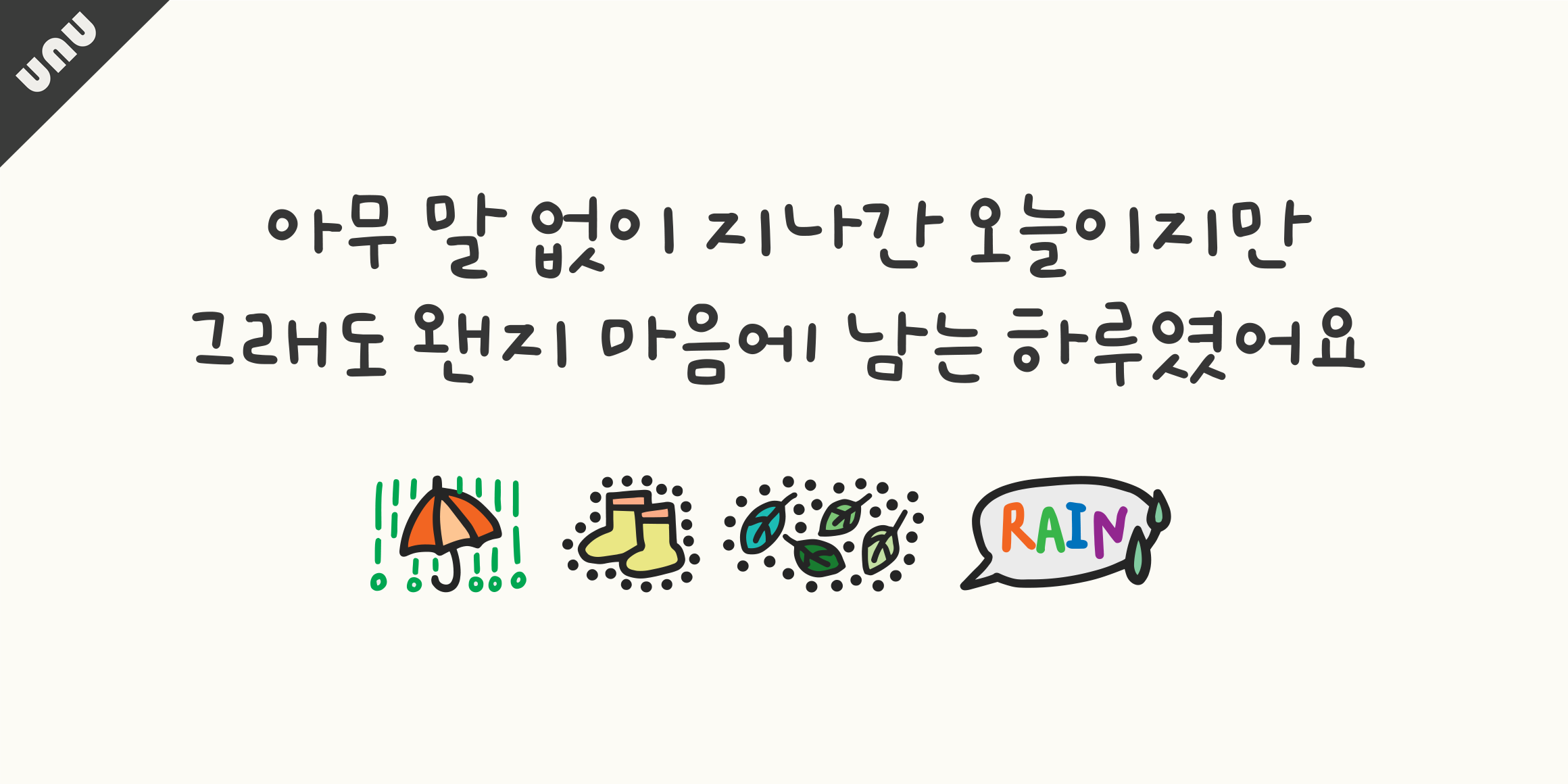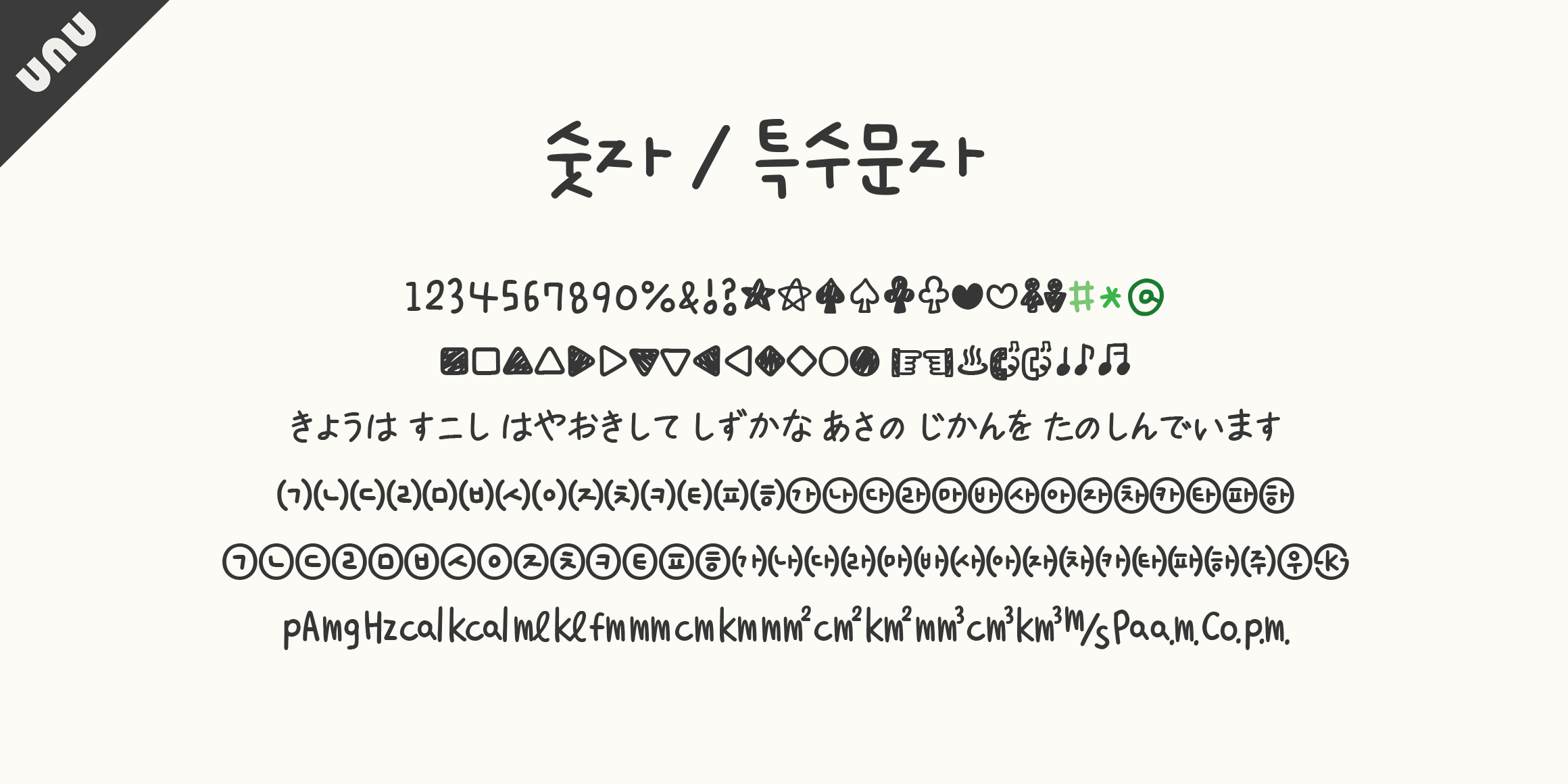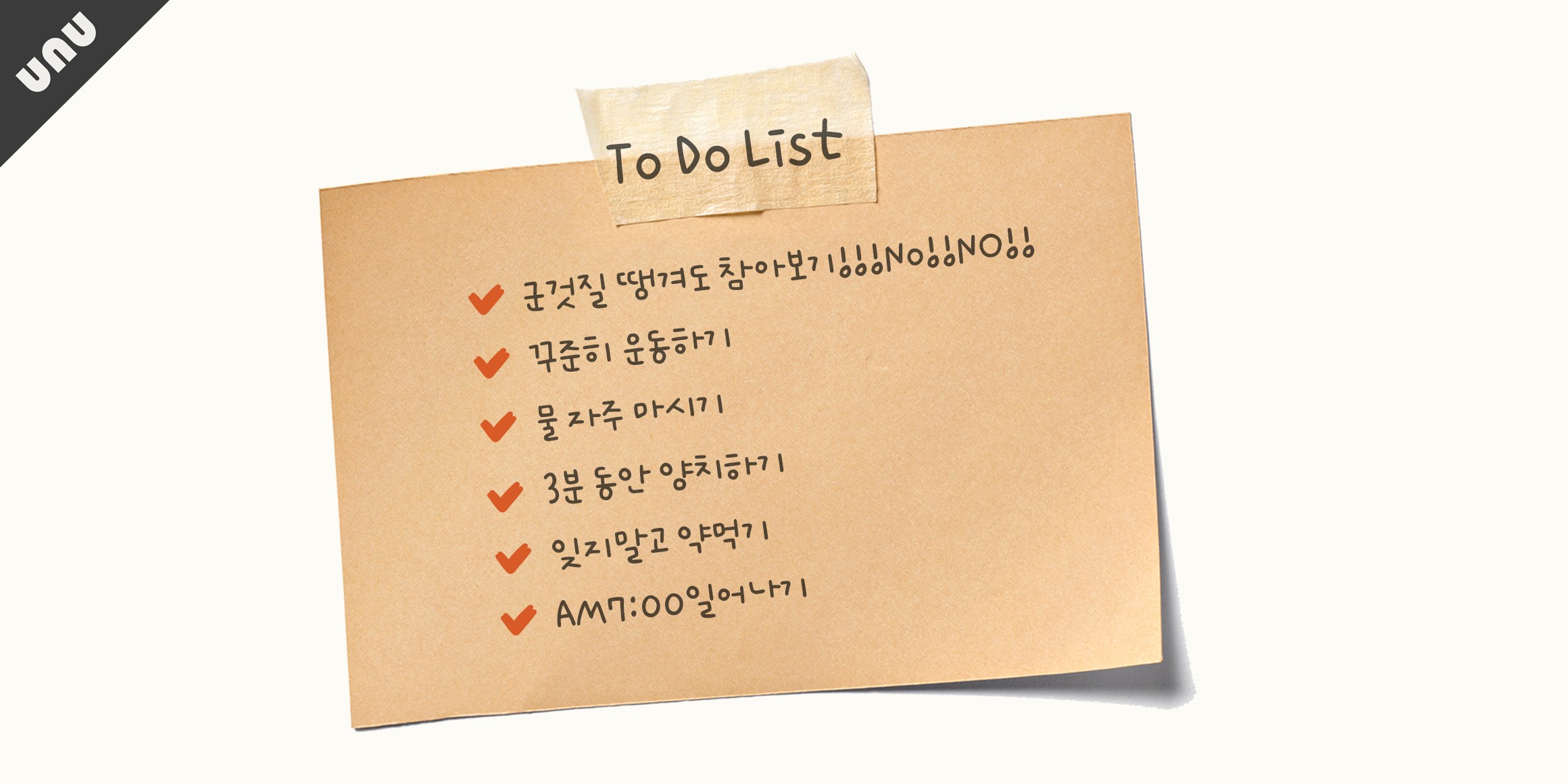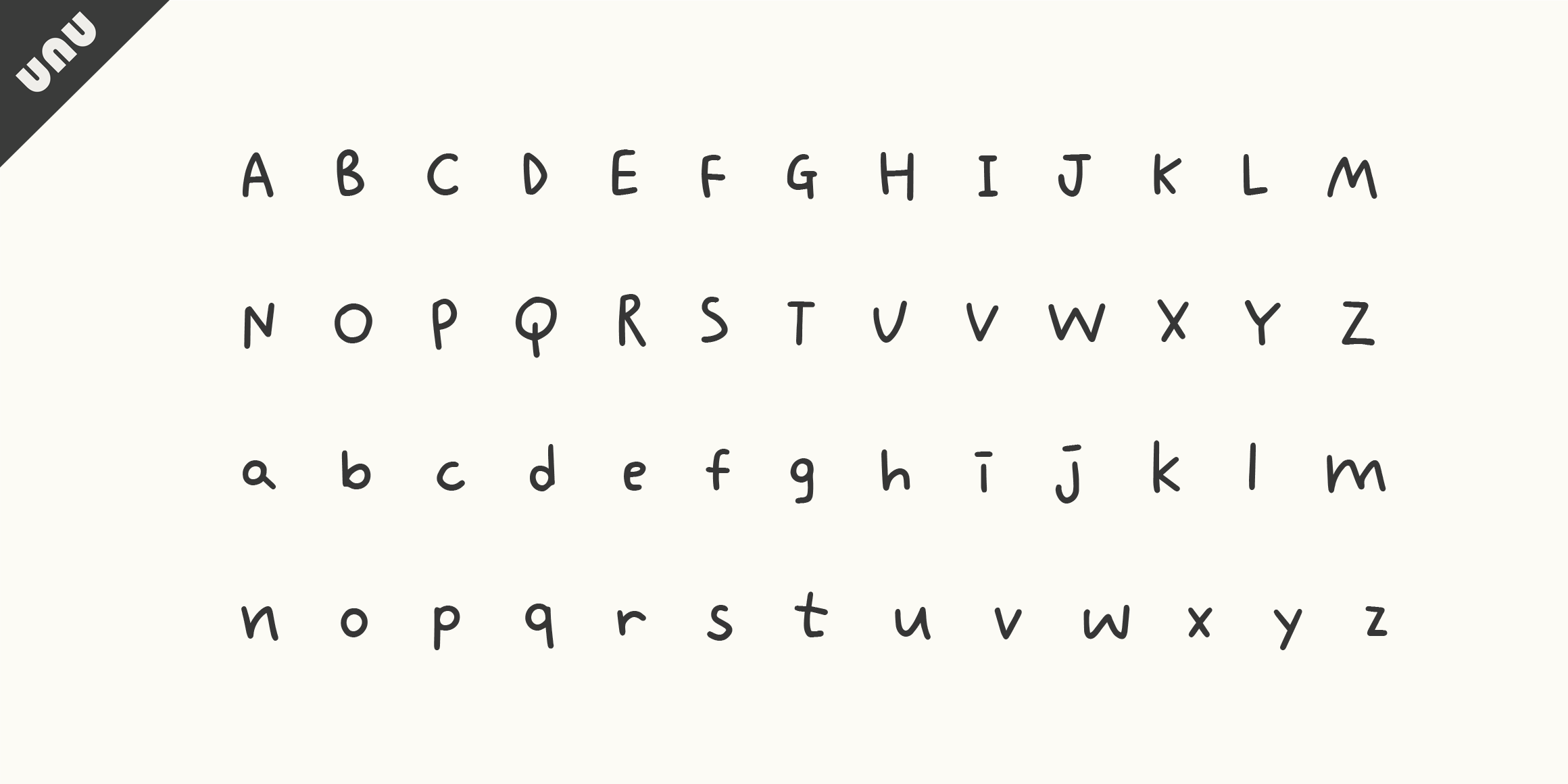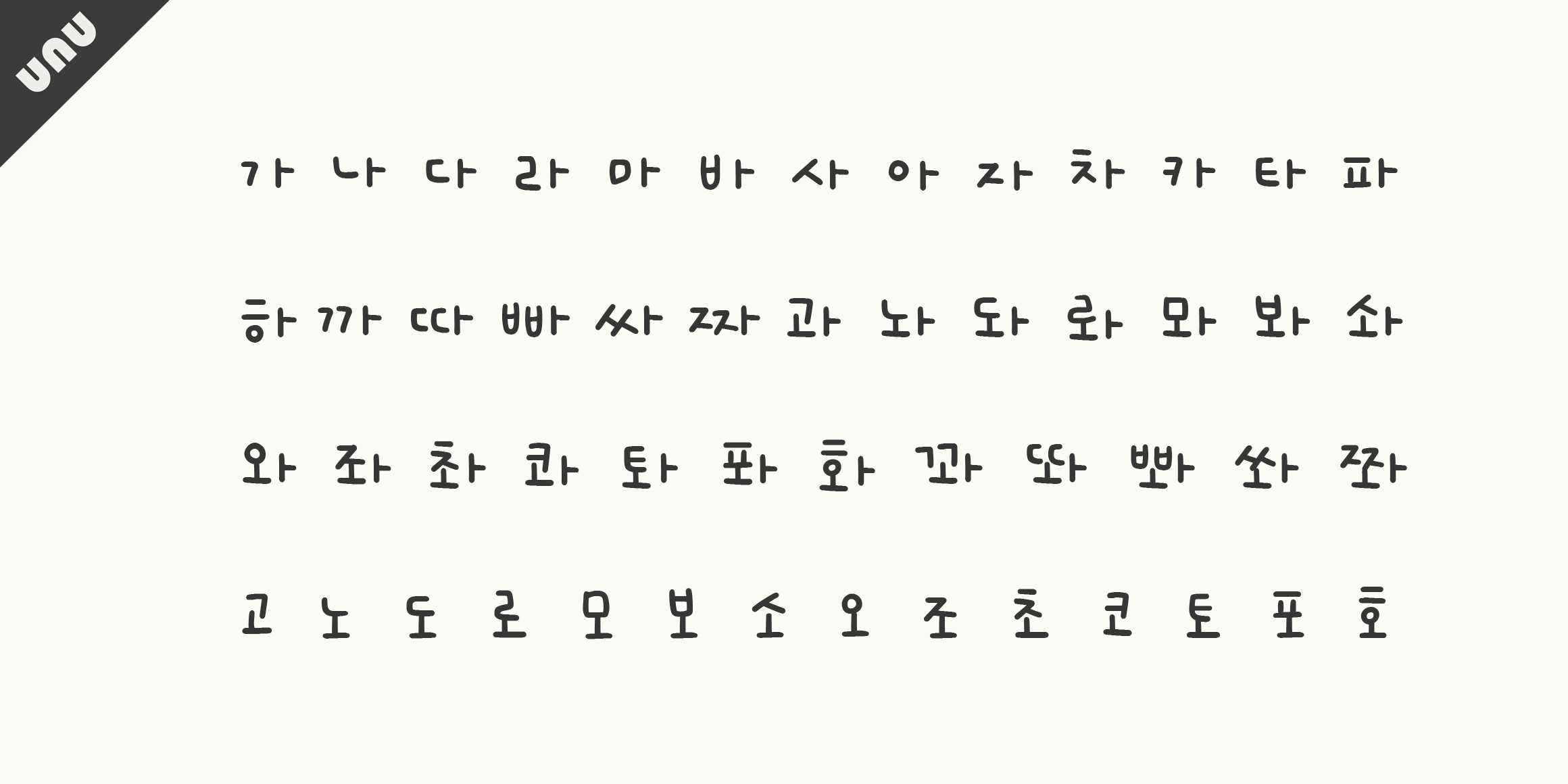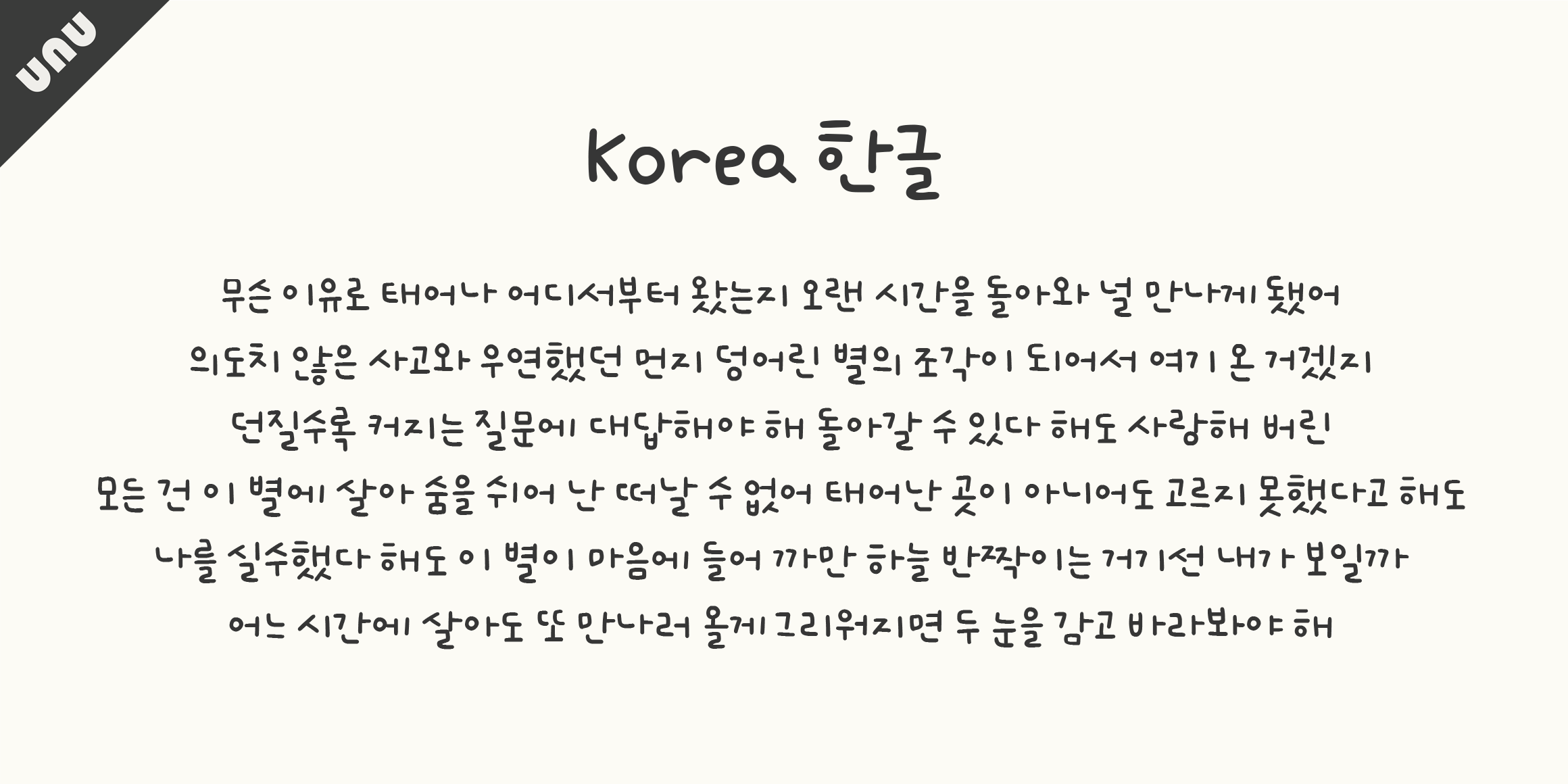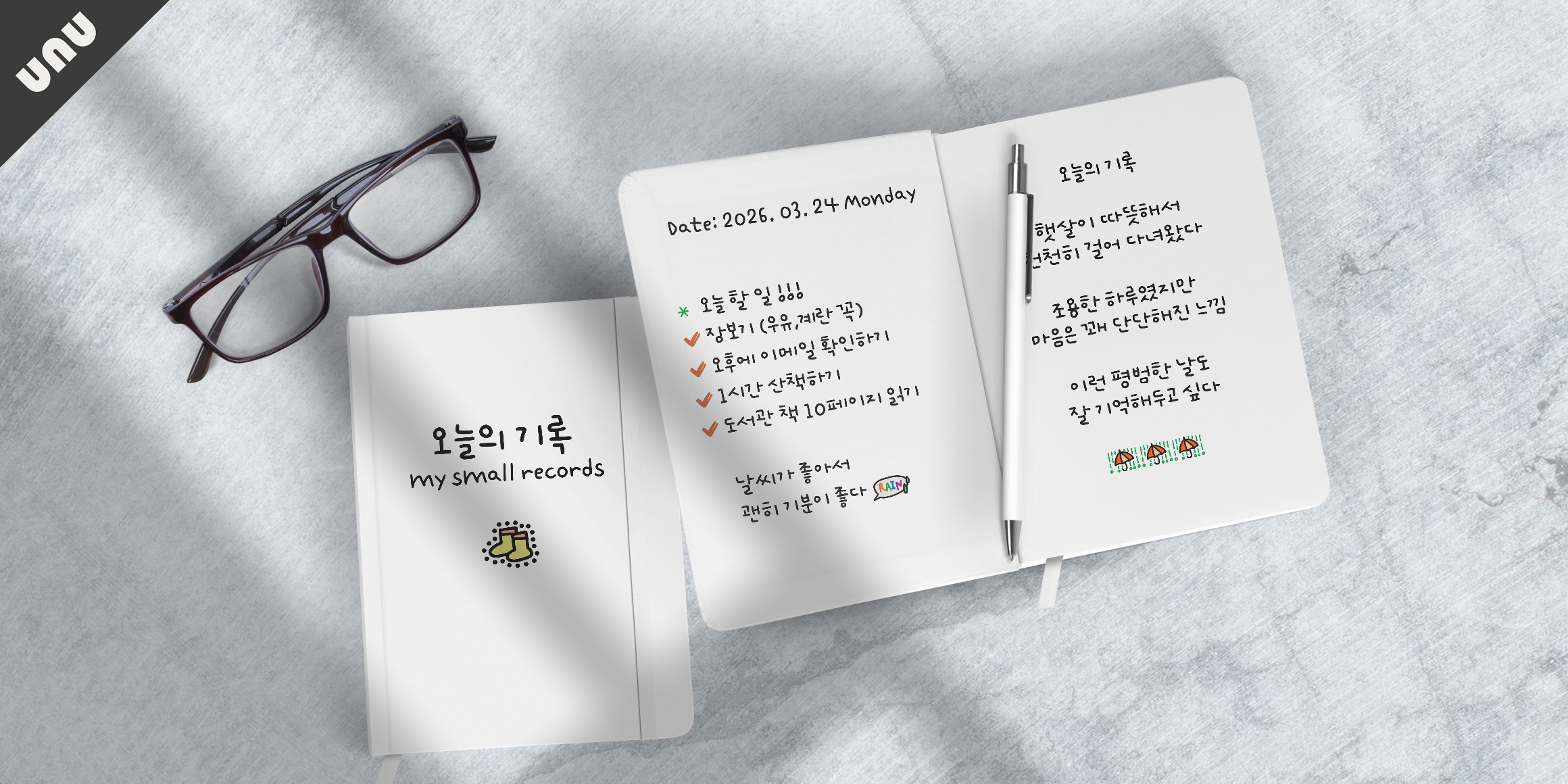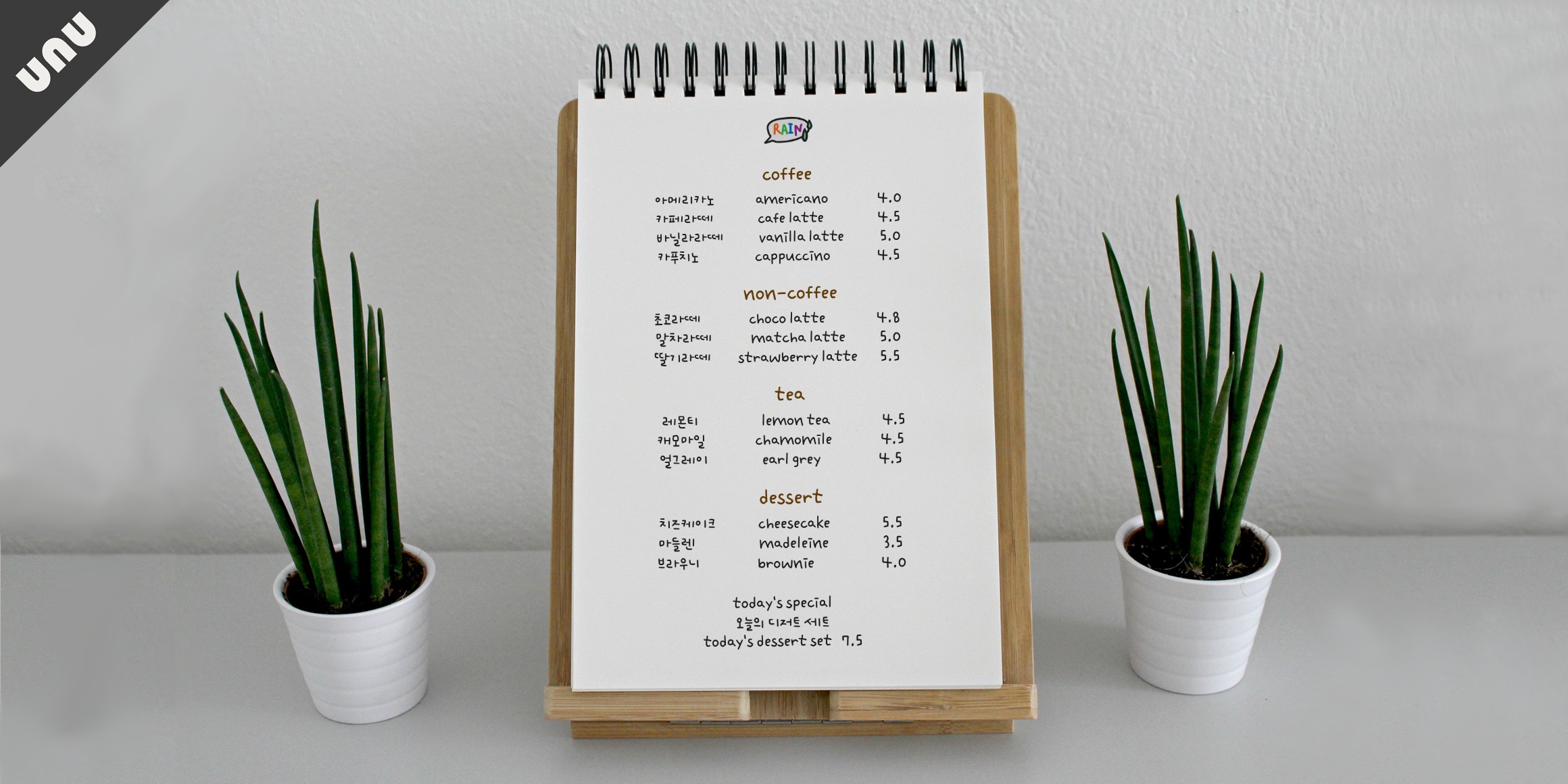
unu초록비
초록 나무들 사이로 내리는 비는 마치 초록비 같아요. 마음의 싱그러움을 느끼게 하는 감성스런 손글씨 서체입니다. 소중한 누군가에게 내 마음을 고스란히 보여주고 싶을때 [unu초록비]서체로 서툴지만 솔직하고 담백한 마음을 전해보는건 어떨까요.
• unu초록비 / unuRainleaf